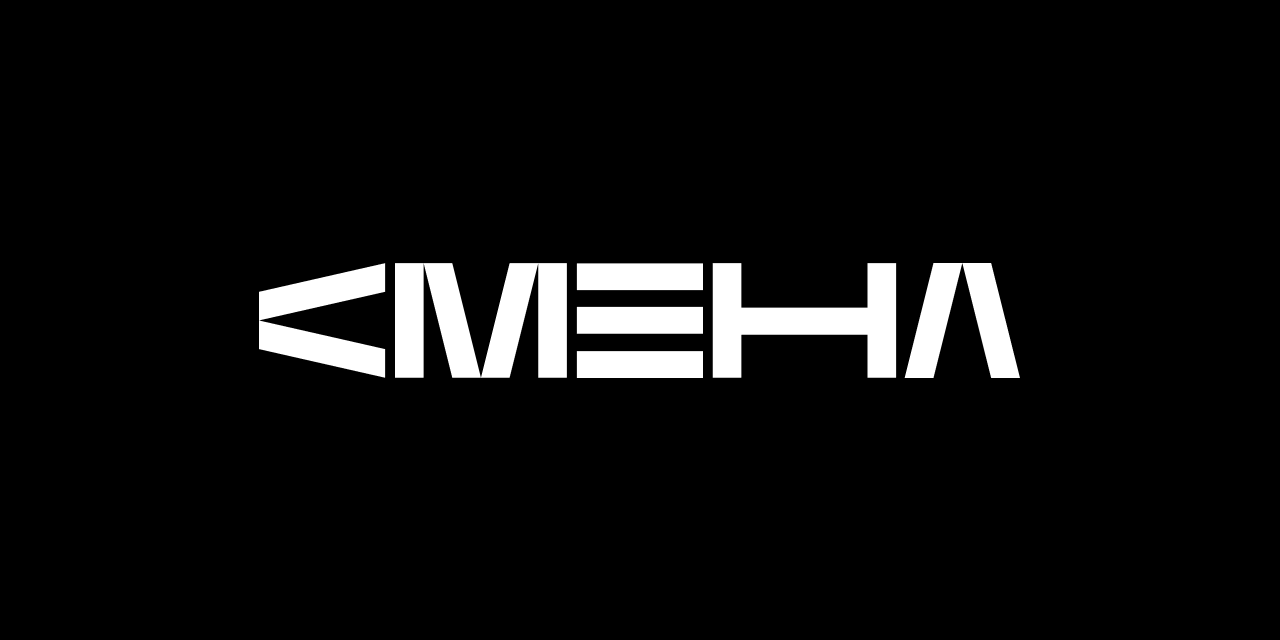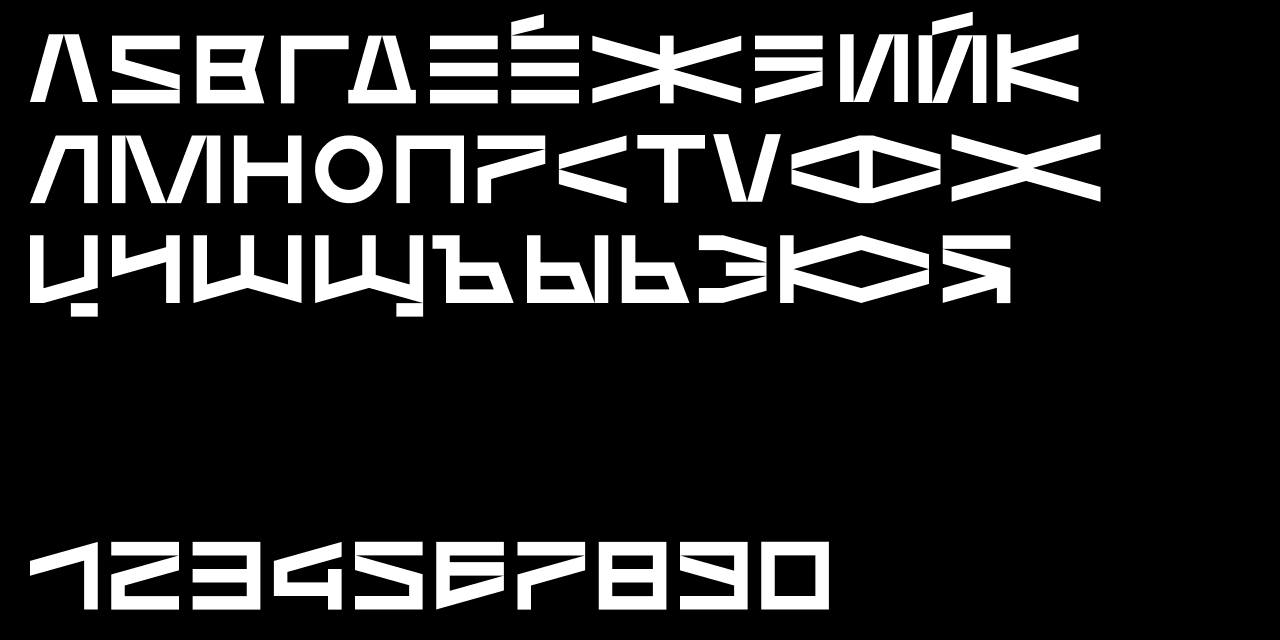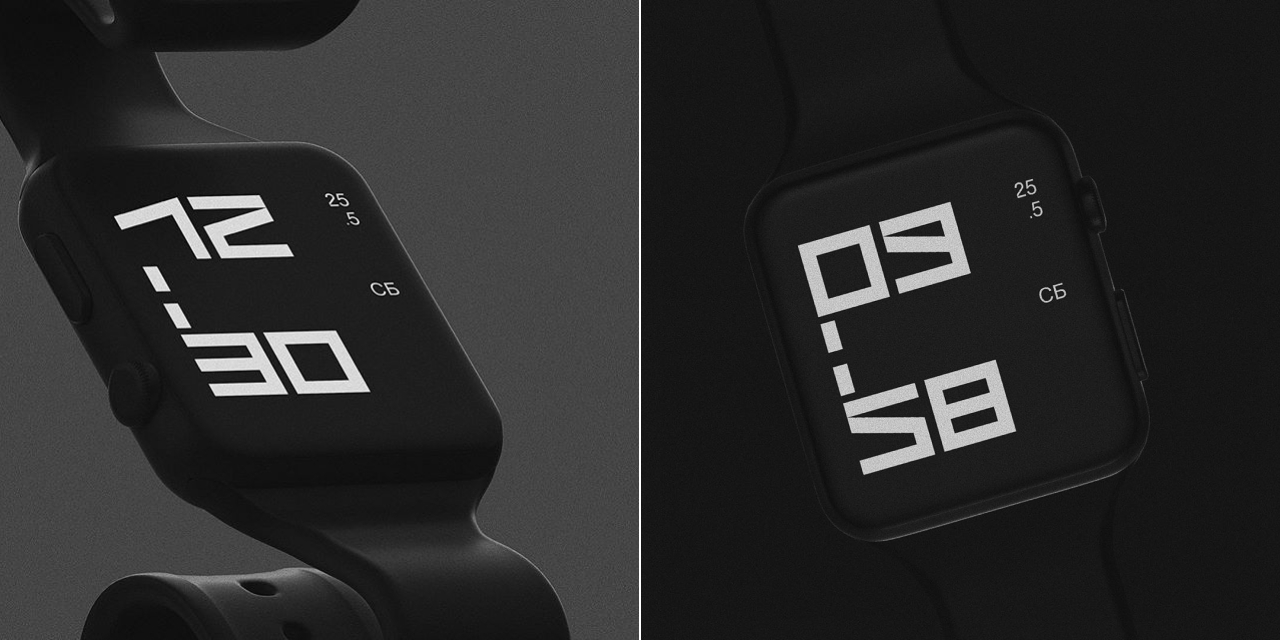
О том, как родились название и айдентика нового игрока российского дизайн-рынка, рассказали специалисты, которые над ними работали.
Компания сервисного дизайна AIC AG недавно заявила о создании дизайн-компании «Смена», которая займется цифровизацией и диджитал-консалтингом крупных государственных проектов. Сейчас главный проект «Смены» — разработка единой дизайн-системы России. Ее будут использовать все официальные государственные сайты и порталы.
Вместе с AIC AG нейминг и фирменный стиль новой компании придумывали команда агентства «Коопирайтеры» и дизайнер Сергей Гуров.
Нейминг
В первую очередь предстояло определиться с названием. В нем хотелось отразить специфику работы и цель команды.
Артем Геллер, глава «Смены»:
Мы займемся государственными проектами в интернете и со временем планируем стать единым центром компетенций по работе государственных институтов в интернете и делать их максимально человечными и сервисными.
На выбор было предложено 37 наименований, все они в той или иной степени соответствовали заявленным критериям: описывали команду дизайнеров-идеалистов, которые хотят сделать мир лучше, подчеркивали опыт и уровень экспертизы, не производя впечатления косности и неповоротливости.
Еще один критерий — название должно быть русским словом, которое просто однозначно воспроизвести и прочесть на латинице.
Вова Носов, директор «Коопирайтеров»:
Нам вообще нравятся отечественные производственные названия, которые использовались еще до того, как всё поросло латиницей. «Заря», «Салют», «Восход» и другие. Коротко, просто и по-русски в хорошем смысле слова.
В них есть тот светлый образ советского инженера, который создает надежные и удобные штуковины из пустоты, огня и хаоса. И насколько мы поняли суть новой команды, им очень подходит сегодняшняя версия этого образа.
Фаворитами стали «Тайга» и выбранная в итоге большинством голосов сотрудников заказчика «Смена».
"Вариант с вечным смыслом изменения. Пришла новая смена на смену тому, что было. Ребята меняют индустрию, а индустрия — мир к лучшему. Одни положительные изменения влекут за собой другие", — так описали название «Коопирайтеры».
Айдентика
Позднее смысл названия дополнили при разработке айдентики. Сергей Гуров придумал сделать акцент на «смену» как временной промежуток (рабочая смена, смена времен года).
Сергей Гуров:
Отправным пунктом для поиска стал сайт AIC AG. Но мне было очень сложно делать что-то нейтральное, универсальное и обезличенное, на что потом можно было бы натянуть айдентику. Хотелось построить вертикальную историю от концепции бренда к айдентике и через сайт к представлению бренда в социальных сетях и на более низких уровнях.
Айдентика окончательно оформилась, когда команда подобрала нужный модульный шрифт. Им стал VLNLTpRawkost_BB, поскольку именно в нем нашлась нужная конфигурация знака, который искали и который всех устроил — это буква С. Шрифт строится на шести линиях, которые совпадают с положением часовых стрелок.
Но набирать более менее длинные слова этим шрифтом не получалось. Поэтому его переработали, сделав более наборным и отрисовав кириллицу.
Сергей изменил 70% букв, толщину, добавил новые правила построения. Сейчас у «Смены» два основных шрифта — один подходит для набора и используется на сайте, другой планируют использовать в рекламных целях и для мерча.
Сейчас айдентика «Смены» утверждена, хотя работа над деталями продолжается. Ближайшая цель — запуск сайта компании. После этого начнется работа, в том числе над мерчем.